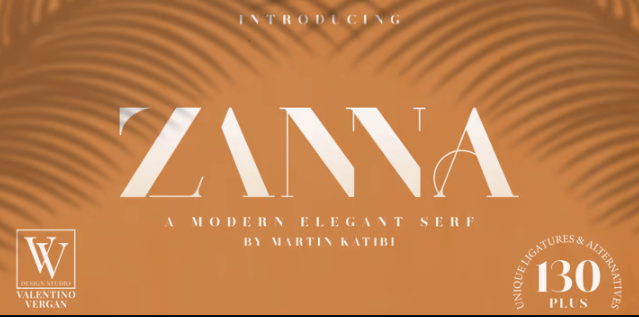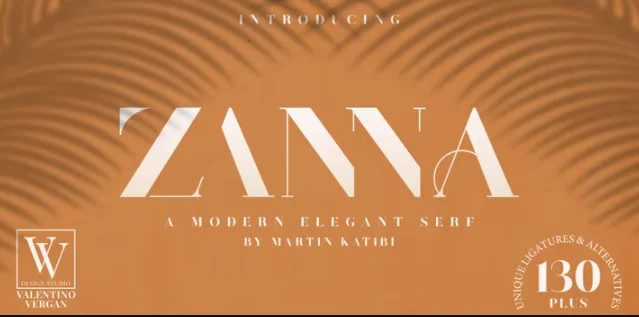
[Myfonts] Zanna Font (2021)
Название: Zanna Font (2021)
Представляем "Zanna" - совершенно новый современный "высококонтрастный" красивый лигатурный шрифт.
Zanna - это стильный современный и элегантный шрифт с засечками, с высоким контрастом и креативными лигатурами. Zanna была вдохновлена знаменитым шрифтом "Didot", что придает ей чувство стиля и моды с оттенком изысканности. Zanna также имеет очень тонкие линии и короткие засечки без скобок, что делает его стильным и шикарным. Шрифт представлен в двух стилях Regular и Stencil, каждый стиль имеет наклонную версию.
Шрифт Zanna создан с использованием возможностей OpenType и включает в себя лигатуры, альтернативы, многоязычную поддержку, цифры и пунктуацию. Чтобы получить доступ к большому выбору лигатур и альтернативных букв, просто выберите лигатуру или альтернативную букву на панели глифов.
Элегантный дизайн Zannas делает его очень универсальным шрифтом, охватывающим широкий спектр проектов, таких как: дизайн одежды, брошюры, журналы, логотип, брендинг, дизайн плакатов, шаблоны Instagram, видео, свадебные приглашения, цитаты, заголовки блогов, плакаты, социальные медиа, реклама и многое другое.
Если вы ищете что-то современное, стильное и шикарное для своего следующего проекта, Zanna - это шрифт для вас.